表層と構造と文字
「表面を作る者を世人は偽善者という。偽善者でも何でもよい。表面を作るという事は内部を改良する一種の方法である」―― 夏目漱石の言葉をサイトに掲げるSurface & Architecture(サーフェス アンド アーキテクチャ)社は、最先端のテクノロジーによって新しい体験を生み出し、そこで生まれる驚きや感動から、人々に「世界の新しい地図」を提示することを目指して活動しています。
「社名の由来は表層と構造です。表層と構造はそんなに離れているものではありません。表面を作ることで中身も変わっていくと思っていますので、私たちはその両方に取り組んでいます。形から入ってもいいから、内面を充実させるという意志を持って仕事をしていくという思いを込めています」と、代表取締役の岡村氏は語ります。
永山氏(中央):イギリス留学中に、大学の図書館にあった唯一の日本語の雑誌のAXIS誌を見て、バイリンガルということを初めて意識しました。合成フォント機能を使わずにひとつの書体で混植までできるというのがとても新鮮でした。
土田氏(左):以前の会社で『このフォントがいいよ』と先輩から聞いていたAXIS Fontを使うことができました。
Surface & Architecture社の制作は主にWebやアプリケーションですが、紙媒体や映像へとその表現媒体を広げています。クライアント企業のサービスがユーザーにとって良い利用体験となるように、サービスのビジョンやコンセプトの提案から、ユーザーが実際に手を触れるところまでを一貫して提供しているのが特徴です。たとえば、NTTドコモのiコンシェルのリニューアルコンセプトの策定への協力やUI/UXデザイン、プロトタイプ開発を行いました。また、オライリー・ジャパンのイベントサイトのデザインや、日本デザイン振興会のWebサイトリニューアルを担当しています。
多くのクライアント企業のプロジェクトでコンセプト策定からデザインまでを担当するSurface & Architecture社は、自社サイトのデザインにAXIS Fontコンデンスを選択しました。サイトのデザインを担当した永山氏は、「サイトリニューアルの際に、ロゴに合う書体を探しました。デバイスの標準フォントのままだと、ロゴとのバランスにおいて、黒味のコントラストが空きすぎてしまうと思ったからです。また、スマートフォンなどの限られた画面の世界に、効率良く情報を表示したいという思いもありました。AXIS Fontコンデンスを選んだのは、ロゴに合うというのも理由のひとつですが、『情報のかたまり感』を調整することなくWebフォントでもそのままで使えるというのが大きな理由です」と語っています。
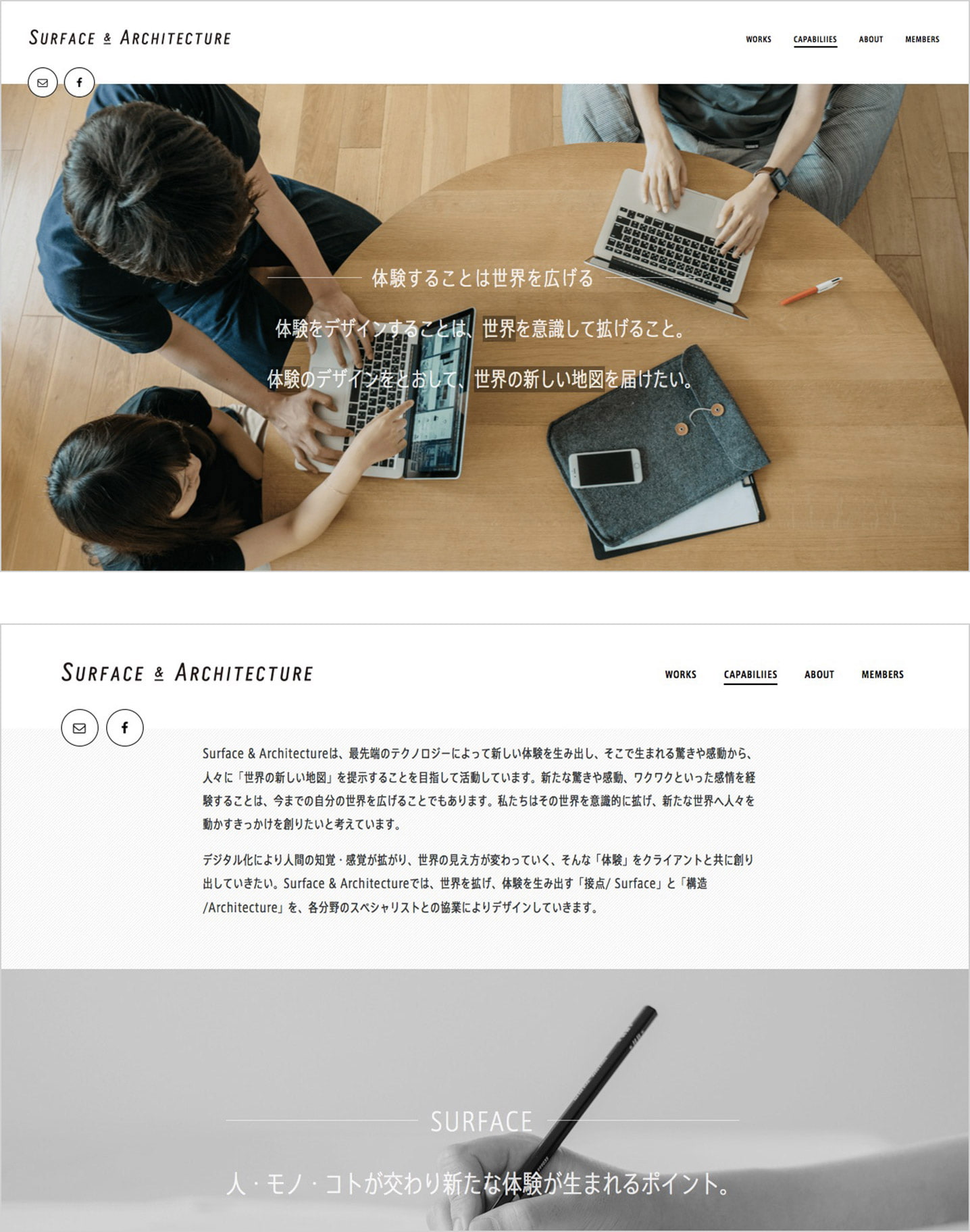
Surface & Architecture社は自社サイトをポートフォリオと位置づけ、全体的には中性的なイメージをもたせながら、コンテンツやページによってウエイトを変えることで、女性的あるいは男性的な印象を出しているといいます。「作品が一番なので、作品がもっとも際立つデザインにしたいと思いました。様々なカラーをもつ作品の邪魔をしないように自社の色を出すことを心がけています。品を保ちつつ必要な情報を入れ、英語との混植でもまとまって見えるように調整をしています。欧文フォントを使うことも考えましたが、最終的にはAXIS Fontが一番しっくりくると思いました。作品ごとにつけている黒地のタグに小さな白抜き文字を使用していますが、この小ささでもつぶれずに読みやすいというのは、発見でした。」(永山氏)
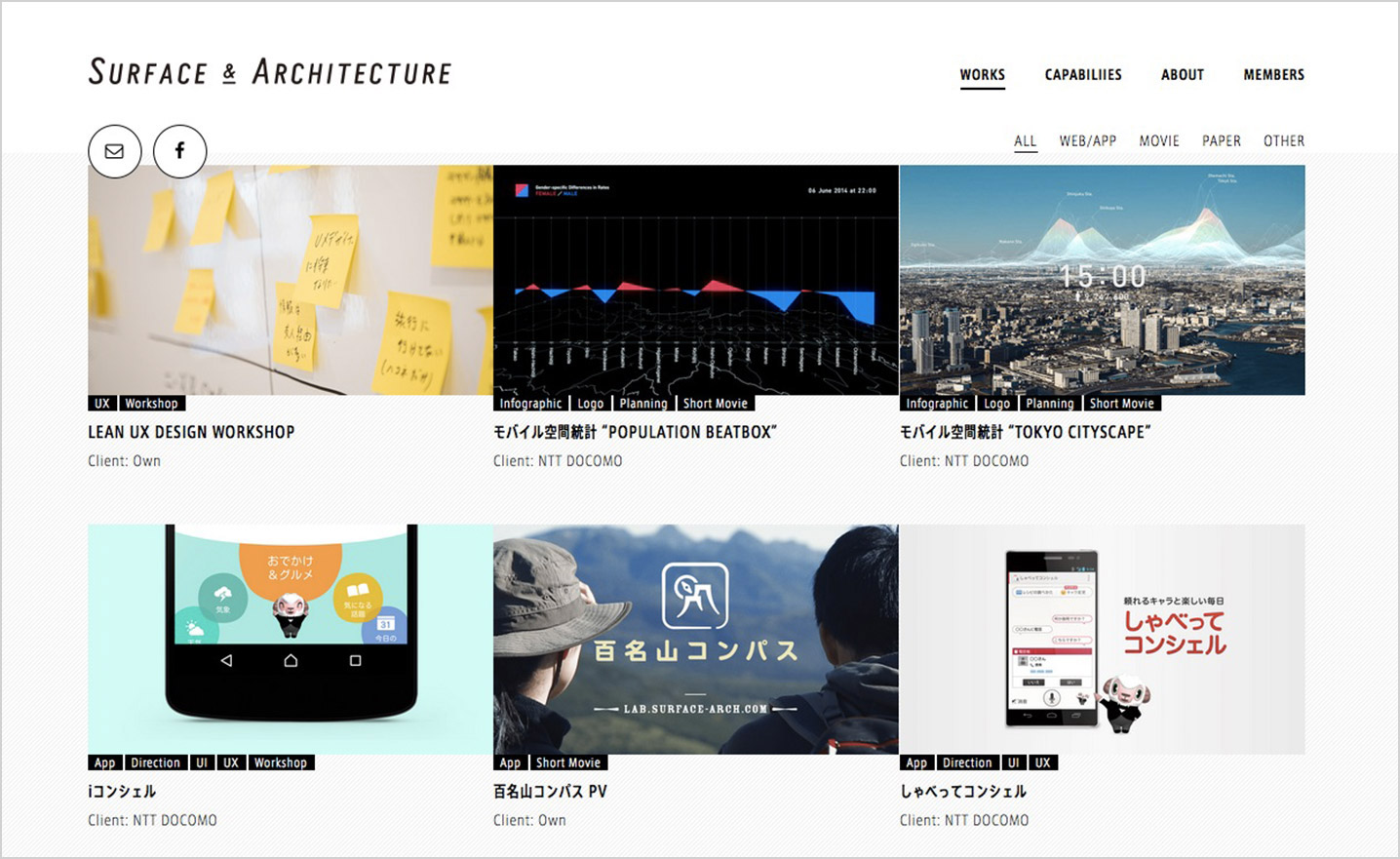
会社紹介のページでは、モノクロ写真にマウスをのせるとカラーになり、テキストが部分的にマーカーされるなど、遊び心を入れた仕掛けが施されています。エンジニアとして実装を担当した土田氏は、「デザイナーの永山と二人で、実際のブラウザ上で確認しながら、一番良い状態でみせるために細かい調整をしました。今回のリニューアルでは、以前の会社で『このフォントがいいよ』と先輩から聞いていたAXIS Fontを使うことができました」と語ります。
Surface & Architecture社では、書類やプレゼンテーションなどでAXIS Fontをコーポレートフォントとして使用しています。「サイトリニューアル後は、デザイナー以外の人にも綺麗になったと言われます。違いを感じてもらえるのは嬉しいですね。装飾過多なテイストにしたくないので、文字で色が出せたのは良かったと思っています。AXIS Fontベーシックは品があって賢いという印象ですが、コンデンスはもう少し力があり個性があって、プロダクト的な表情がでます。そこが会社のブランドイメージにもとても合っていると思います」(岡村氏)